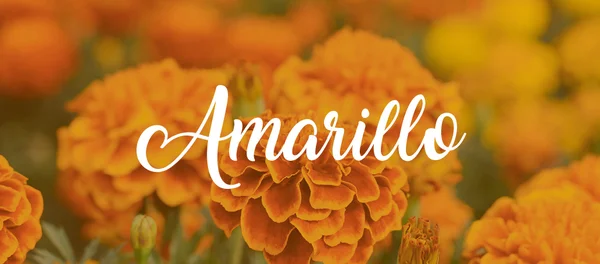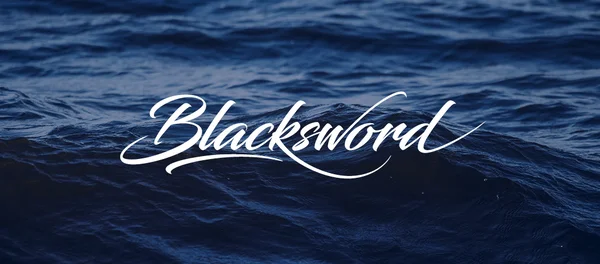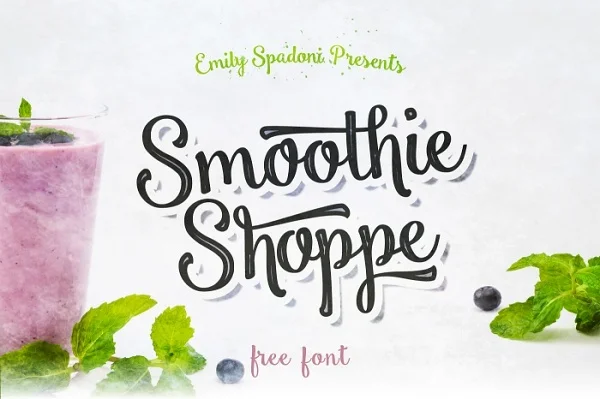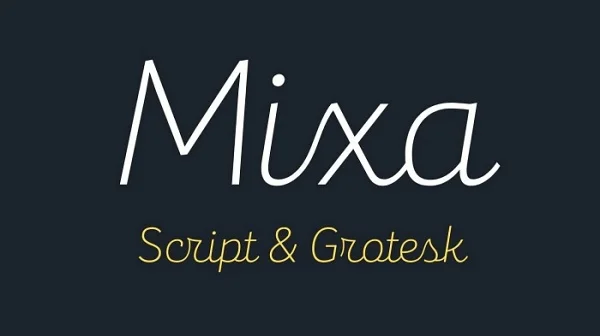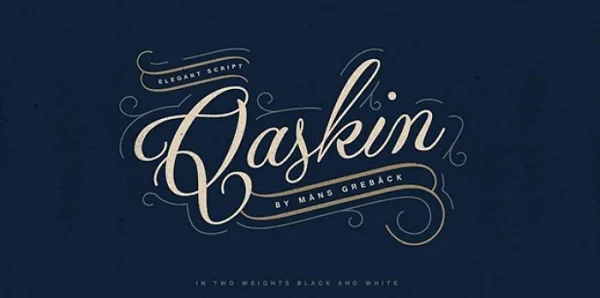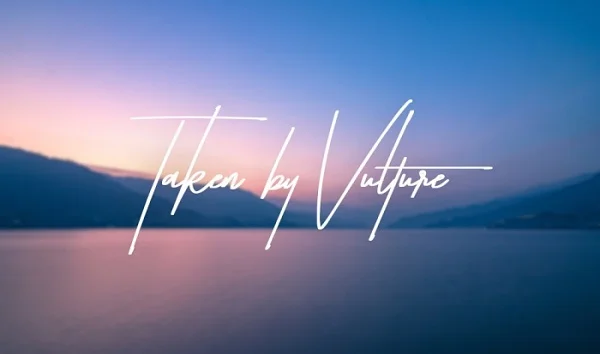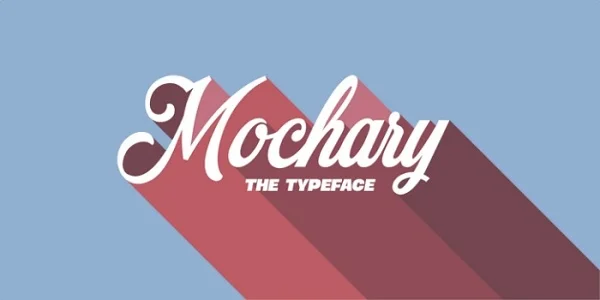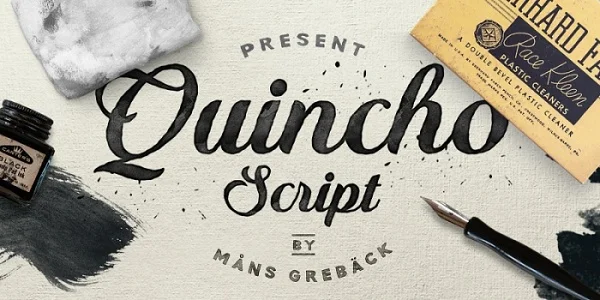
Là 1 designer, chắc hẳn bạn đã nhiều hơn một lần sử dụng font Script cho các sản phẩm sáng tạo của mình, đây là font chữ đẹp và được sử dụng nhiều. Nhưng nếu như bạn chỉ mới bắt đầu con đường thiết kế của mình và chưa có nhiều thông tin về font Script hay có cho mình những bộ Script font Việt hóa đẹp thì bài viết này chính là dành cho bạn. Printgo xin giới thiệu sơ lược về font Script và gửi đến các bạn link download font Script Việt hoá miễn phí ở cuối bài
Font Script là font chữ có cấu trúc mảnh và được làm nổi bật bởi các đường cong như hình vẽ. Tuy nhiên font chữ này sẽ khá là khó sử dụng và có một vài hạn chế nhất định trong các thiết kế dùng cho in ấn.
Sử dụng quá nhiều font Script cho nội dung văn bản sẽ khiến nó trở nên rối mắt và khó đọc, gây khó chịu cho người nhìn. Mẫu font này thường được dùng trong các loại thiệp mời đám cưới, bìa sách lãng mạn, poster phim,...
Script font Việt hoá rất được các designer ưa chuộng. Vì vậy Printgo xin gửi đến các bạn link download miễn phí TOP 10+ Script font Việt hóa đẹp nhất năm 2021 ở cuối bài viết. Trước đó, hãy cùng điểm qua một vài mẫu font Script Việt hoá đẹp và mới nhất:
Đây là 1 font chữ thư pháp được Francis Studio thiết kế. Nó rất phù hợp cho tiêu đề thiệp cưới hoặc văn phòng phẩm nhờ sự sinh hoạt và các nét đơn giản của nó. Font chữ này sẽ hoàn hảo hơn nếu được kết hợp cùng các font Serif cổ điển như EB Garamond.
Blacksword là một phông chữ script sắc nét có tính năng swifelike swashes được thiết kế bởi Youssef Habchi. Kiểu chữ này được sử dụng tốt nhất làm tiêu đề có kích thước lớn, vì các dấu gạch ngang có thể khó đọc ở kích thước nhỏ. Nó sẽ trở nên hoàn hảo hơn kết hợp cùng một font sans serif như Nunito.
Thêm một liên lạc viết tay vào thiết kế của bạn với phông chữ tập lệnh brush có texture này. Broadcast Matter sẽ đẹp hơn khi đi với một font serif như Source Serif Pro.
Dancing Script được thiết kế bởi Impallari Type, bắt chước các chuyển động của một vũ công chuyên nghiệp, thanh thoát và uyển chuyển. Khi Dancing Script đi cùng với font Sans Serif như Lato sẽ cho một sự tương phản vui tươi.
Phông chữ Francisco do Premier Graphics nắm quyền sở hữu. Đây là một phông chữ có đường nét vẽ tay rất thích hợp để làm chữ ký.
Golden Plains, được sản xuất bởi BLKBK Fonts, tạo ra một cảm giác ma mị, kỳ quái với họa tiết tinh tế và dạng chữ hữu cơ.
Great Vibes, một font script tinh tế, tao nhã được sản xuất bởi TypeSETit.
Font chữ này do StereoType thiết kế và sở hữu. Những chữ cái có các đường nét dày nổi bật dựa trên những cảnh quan rừng nên thơ và mơ mộng.
Font chữ brush này cũng do StereoType thiết kế và có các ký tự chữ dày được vẽ bằng một dấu Stabilo. Mark My Words với kết cấu tinh tế có hiệu ứng vẽ tay nên hoàn hảo cho việc kết hợp với các nền ảnh chủ đề du lịch, khám phá.
Phong cách kịch bản chữ ký của Matsury thể hiện rất đẹp khi áp dụng cho hình ảnh nền hoa để tạo cảm giác sang trọng, đẳng cấp.
Qaskin là một font chữ thanh lịch và hiện đại, mang lại cảm giác tinh tế với các đường nét mảnh mai, phù hợp cho thiết kế thời trang, logo và các dự án sáng tạo cần sự sang trọng.
Với phong cách grunge và đậm chất retro, Taken by Vulture là font chữ hoàn hảo cho những thiết kế mang tính phá cách, đậm chất nghệ thuật đường phố và phong cách vintage.
Font chữ Smoothie Shoppe gợi lên sự vui tươi, ngọt ngào với các nét chữ tròn trịa và mềm mại, lý tưởng cho các thiết kế liên quan đến thực phẩm, đồ uống hoặc các sản phẩm dành cho giới trẻ.
Blushes mang đến vẻ đẹp lãng mạn và nữ tính với những đường nét nhẹ nhàng, phù hợp cho các dự án về thời trang, thiệp mời đám cưới, hoặc các sản phẩm chăm sóc sắc đẹp.
Mixa là font chữ hiển thị với thiết kế độc đáo và năng động, có các ký tự hình học mạnh mẽ, phù hợp cho các thiết kế hiện đại, thương hiệu công nghệ hoặc các dự án mang tính sáng tạo cao.
Mochary là một font chữ với phong cách viết tay mềm mại và bay bổng, mang lại cảm giác tự nhiên, ấm áp, rất thích hợp cho các thiết kế cá nhân, blog, hoặc bao bì sản phẩm thủ công.
Quincho nổi bật với các đường nét dày dặn và cổ điển, mang đậm phong cách chữ cái Latin, lý tưởng cho thiết kế poster, bìa sách hoặc logo cần sự mạnh mẽ và uy nghiêm.
Safir Script là một font chữ viết tay uyển chuyển và thanh lịch, hoàn hảo cho các thiết kế thiệp mời, thương hiệu cao cấp, hoặc các dự án nghệ thuật đòi hỏi sự tinh tế.
Tropical Sweet mang đậm hơi thở nhiệt đới với những đường nét tròn trịa và tươi vui, lý tưởng cho thiết kế bao bì sản phẩm mùa hè, poster lễ hội hoặc thương hiệu đồ uống.
TT Cottons Light là font chữ sans-serif nhẹ nhàng và tinh tế, với các đường nét đơn giản, hiện đại, phù hợp cho thiết kế giao diện web, tài liệu công ty hoặc các dự án tối giản.